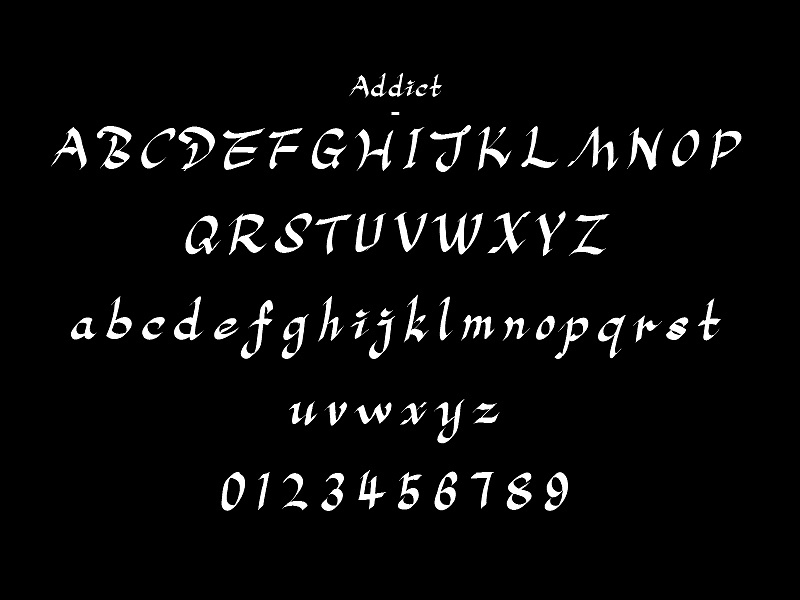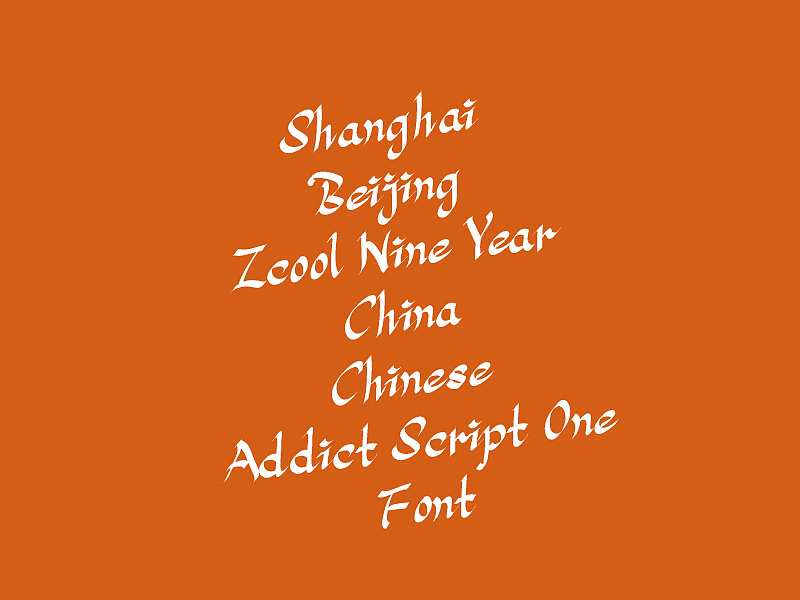
【Addict Script One】手写风格,oldstyle罗马正体衬线元素
这套字库是手写体的风格,但是加入了oldstyle罗马正体的衬线元素,颇具一番风,这套字库除了字母和数字外还包括常用的标点和符号,能够广泛用于正文字体和海报等地方。
Addict Script One看似随意,实际上也遵循了罗马正体的规则,有标准的升部线、大写线和降部线,只是字形随意洒脱,有另类风,可以免费商用。